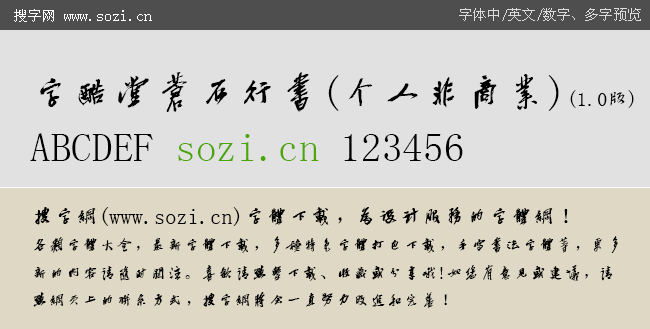
字酷堂蒼石行書(個人非商業(yè))
搜字網(wǎng)提供一款字酷堂蒼石行書(個人非商業(yè))中文書法字體下載,字酷堂蒼石行書是一款非常漂亮的書法字體,字體飄逸大方,結(jié)構(gòu)合理沉穩(wěn),整體字形非常大氣,適合應(yīng)用于廣告設(shè)計、名片設(shè)計、包裝印刷、海報設(shè)計等應(yīng)用。